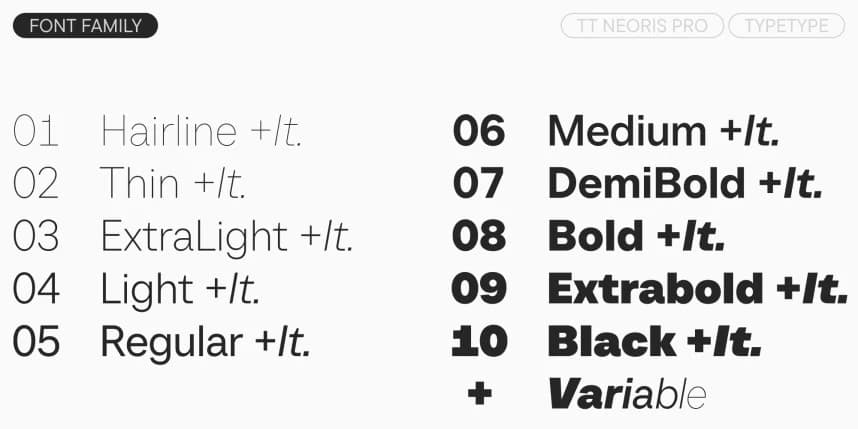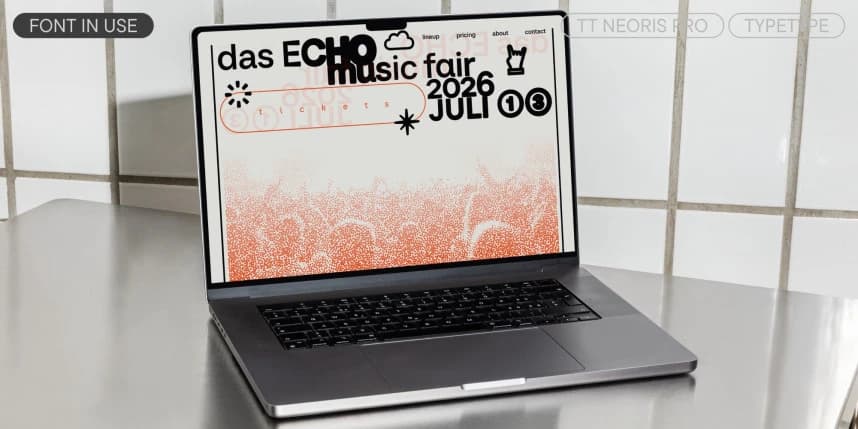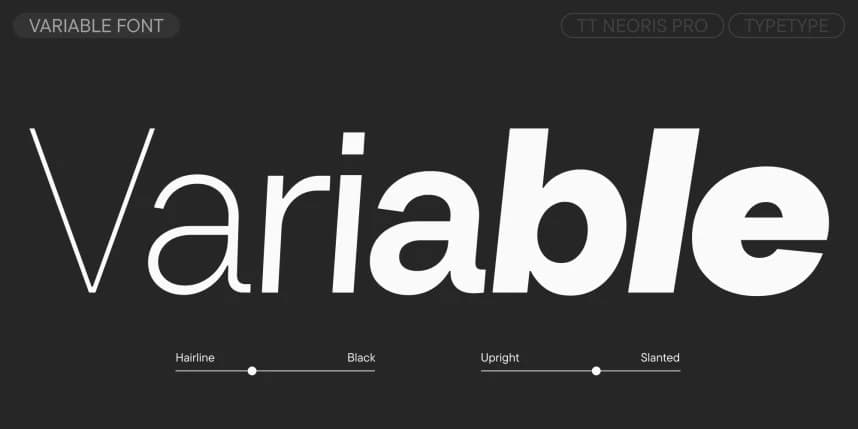
TT Neoris Pro Font Family
TT Neoris Pro Yazı Tipi Ailesi. TT Neoris Pro sürümü 2.000—artık Yunanca, Arapça ve Vietnamca desteğiyle! TT Neoris Pro, evrensel kullanım için tasarlanmış özlü bir neo-grotesk yazı tipi. Bu yazı tipi ailesini iki buçuk yıl boyunca geliştirdik.
TT Neoris Pro Yazı Tipi Ailesi. TT Neoris Pro sürüm 2.000—artık Yunanca, Arapça ve Vietnamca desteğiyle! TT Neoris Pro, evrensel kullanım için kısa ve öz bir neo-grotesk yazı tipidir. Bu yazı ailesini iki buçuk yıl boyunca geliştirdik.